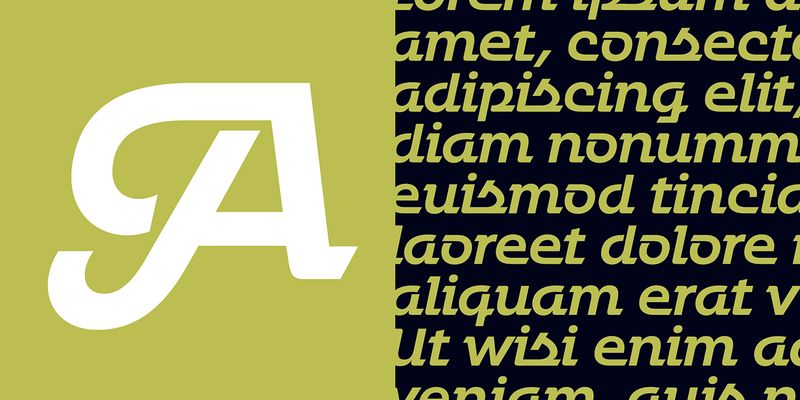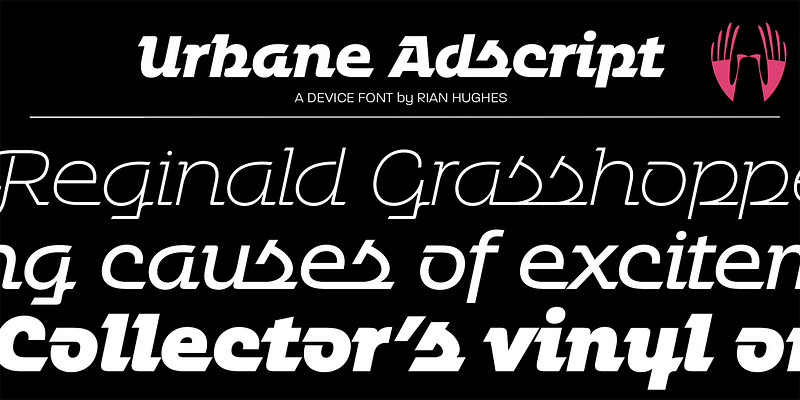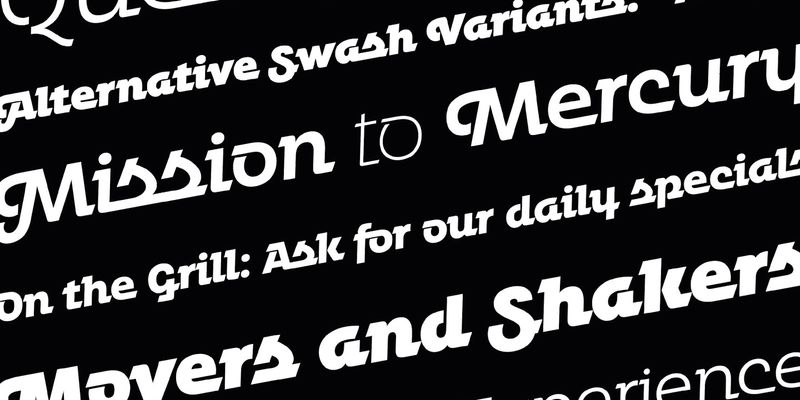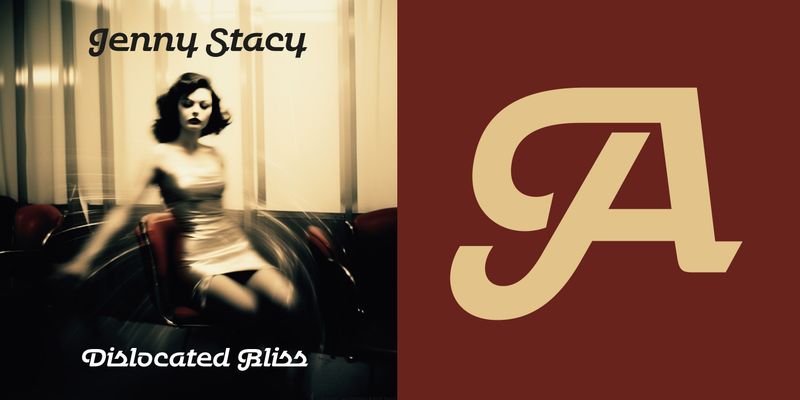
En universalfamilj med många användningsområden. Den större x-höjden innebär obehindrad läsbarhet även i små storlekar, och alla vikter och stilar – kursiv, skript, rundade, grova – gör detta till en stor och mångsidig familj.